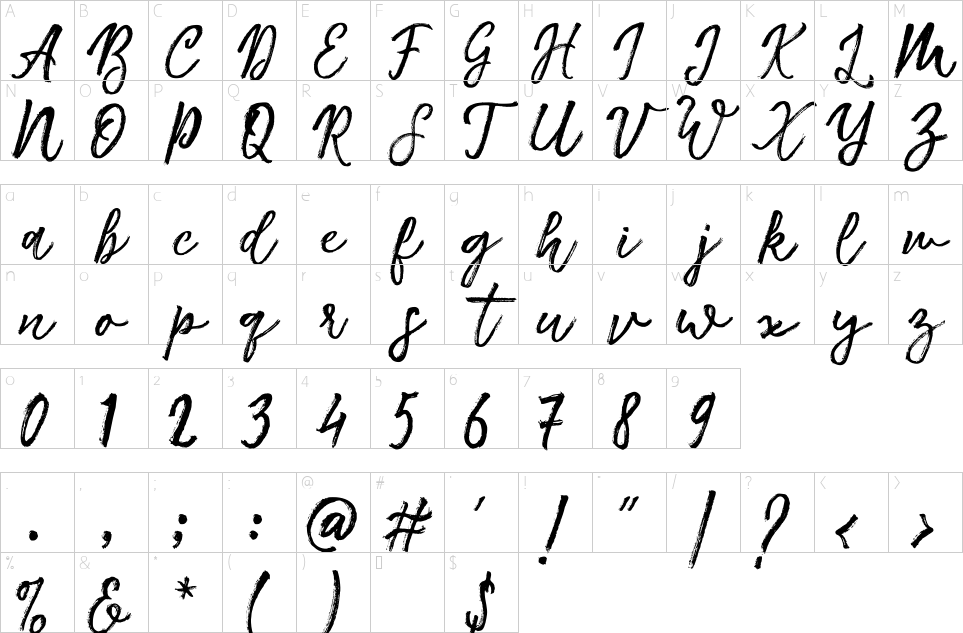
Anstolina Script Font – Download Grátis
Anstolina Script é uma fonte elegante e fluida, ideal para estilos de design que valorizam graciosidade e personalidade. Desenvolvida pelo estúdio Stripes Studio, essa fonte vem em versões para Windows e Mac, permitindo que designers de gráficos a utilizem em diversos projetos. Com traços delicados e linhas suaves, Anstolina Script é perfeita para criar texturas elegantes e estilos de design em formato digital. Sua usabilidade no design gráfico, sobretudo em seções de texto, nomes de produtos e design de sites, torna-a uma opção indispensável para designers. Com downloads de 1,335 vezes, Anstolina Script demonstra seu valor e popularidade entre os designers digitais. Experimente incorporar Anstolina Script em seus projetos para agregar um toque único e refinado ao seu trabalho.